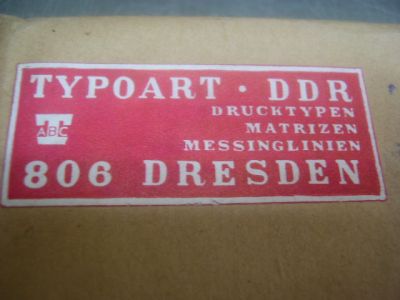
Minima von Karl-Heiz Lange
Die "Minima" von Kalr-Heinz Lange hätt' ich gern und würde noch viel lieber wo es die zu kaufen gibt?
Vielleicht solte man dem Herrn Lange mal vorschlagen, die Schrift der Öffentlichkeit zum Verkauf anzubieten.
ich glaube, der herr lange hat leider keine rechte darauf.
Aber irgendwer hat doch TypoArt übernommen nach der Wiedervereinigung? Ich weiß definitiv, daß sie 1989 noch Bleisatz im Osten verkauft haben. Ein ostdeutscher Drucker hat damals für 19.000 Ostmark zugeschlagen, weil man ihm eingeredet hatte, er könne damit nach der Wiedervereinigung mit seiner Buchdruckerei richtig gut einsteigen. Das war dann natürlich leider nichts.
Irgendwer muß doch die Matrizen haben.
Ah.. vielleicht dieses Typo-Dings-Zentrum für Bleisatz und Buchdruck Leipzig? Wie heißt denn das noch?
meinst du das Museum für Druckkunst Leipzig? Es kann gut sein, dass dort Bleilettern der Minima lagern. Aber ich glaube, Crazygen sucht die Minima als digitalen Font, oder?
Auf den TypoTagen 2004 sprachen mehrere Schriftgestalter, die zu Zeiten der DDR für den »VEB Typoart« Schriften erschaffen haben, unter anderem auch Karl-Heinz Lange. Wenn ich mich an die damaligen Wortbeiträge richtig erinnere, ist es so, dass die Rechte vieler Schriften, die von der Typoart verlegt wurden, auf die Person übergingen, die nach dem Zusammenschluss von BRD und DDR die »Typoart GmbH« (wie sie dann hieß) aufgekauft hat. Diese Person hat sich wohl nach dem Konkurs abgesetzt. Sie ist aber immer noch Inhaber der Rechte. Daher können selbst die ehemaligen Typoart-Designer ihre eigenen Schriften nicht vermarkten. Daher wird man wohl keine digitale Version der Minima finden.
meinst du das Museum für Druckkunst Leipzig? Es kann gut sein, dass dort Bleilettern der Minima lagern. Aber ich glaube, Crazygen sucht die Minima als digitalen Font, oder?
Auf den TypoTagen 2004 sprachen mehrere Schriftgestalter, die zu Zeiten der DDR für den »VEB Typoart« Schriften erschaffen haben, unter anderem auch Karl-Heinz Lange. Wenn ich mich an die damaligen Wortbeiträge richtig erinnere, ist es so, dass die Rechte vieler Schriften, die von der Typoart verlegt wurden, auf die Person übergingen, die nach dem Zusammenschluss von BRD und DDR die »Typoart GmbH« (wie sie dann hieß) aufgekauft hat. Diese Person hat sich wohl nach dem Konkurs abgesetzt. Sie ist aber immer noch Inhaber der Rechte. Daher können selbst die ehemaligen Typoart-Designer ihre eigenen Schriften nicht vermarkten. Daher wird man wohl keine digitale Version der Minima finden.
Ja, genau. Ich meinte das Museum für Druckkunst Leipzig.
Wer ist "die Person"? Da sie sicher im Handelsregister stand bzw. nun in den öffentlich zugänglichen Akten des zuständigen Insolvenzgerichtes, dürfte diese Information ebenfalls öffentlich sein.
Das Museum für Druckkunst Leipzig arbeitet nicht (mehr) sehr eng mit den Kollegen in Darmstadt/Frankfurt zusammen. Was ich als sehr schade empfinde. Es gibt ja nur noch eine Handvoll Schriftgießer.
Daher wird man wohl keine digitale Version der Minima finden.
Doch doch, die gängigen Typoart Schriften einschließlich der Minima waren bereits digitalisiert. Herr Lange hat sie nach seinen eigenen Angaben auf seinem Rechner. Einige andere hat die Hochschule für Grafik und Buchkunst Leipzig.
Es traut sich nur leider niemand der Typoart-Designer die Schriften selbst wieder rauszubringen, auch wenn die rechtlichen Bedenken alle völlig unsinnig sind.
Ich habe vor einigen Jahren ca. 800 kg Material von TypoArt aufgekauft. Schriftschnitte der Super-Grotesk, Splendor, Erler-Versalien. Und jede Menge Blindmaterial.
Was die Copyrights angeht, wäre vielleicht auch noch die Frage, welche Ansprüche daran die Nachfahren von Besitzern der zwangskollektivierten Schriftgießereien vielleicht haben könnten wie die der Schriftguß A.-G. Vielleicht will man an dieser Thematik einfach nicht rühren, weil man einen jahrzehntelangen Rechtstreit befürchtet.
Gerade bereite ich einen Andruck der Garamond mager kursiv der TypoArt, Dresden vor.
Beim Handsetzen hat man ein völlig anderes, sinnlicheres Gefühl als beim Eintasten von Zeichen in einen EDV-Arbeitsplatz. Daß Ihr das im Normalfall nicht mehr erlebt, ist traurig. Man bekommt ein sehr nahes Gespür für die Schrift.
Diese TypoArt-Garamond ist unglaublich schön.
Die vielen Ligaturen und die zusätzlichen Mediaeval-Ziffern..
Was ich mich nun frage:
Warum hat TypoArt diese Garamond nicht auch in der damaligen BRD angeboten? Sie hätte ohne Probleme neben der Garamond von Stempel bestehen können. Hat TypoArt überhaupt im westlichen Ausland angeboten bzw. anbieten dürfen? Die Kommunisten waren doch heiß auf Devisen, wäre doch ein gutes Geschäft gewesen.
Ob ich die Garamond mager kursiv von TypoArt auch auf meiner Webseite hochlade in der Schriftensammlung dort? Joh, sicher.. zum 1.Mai - Tag der Arbeit (paßt doch.. :-)
Ich hab jetzt schon einige Bücher gelesen, die in der Tschörtner-Antiqua gesetzt waren und muss sagen, dass sie sich sehr gut als Mengenschrift macht. Zu schade, wenn man den TypoArt Schatz nicht heben könnte.